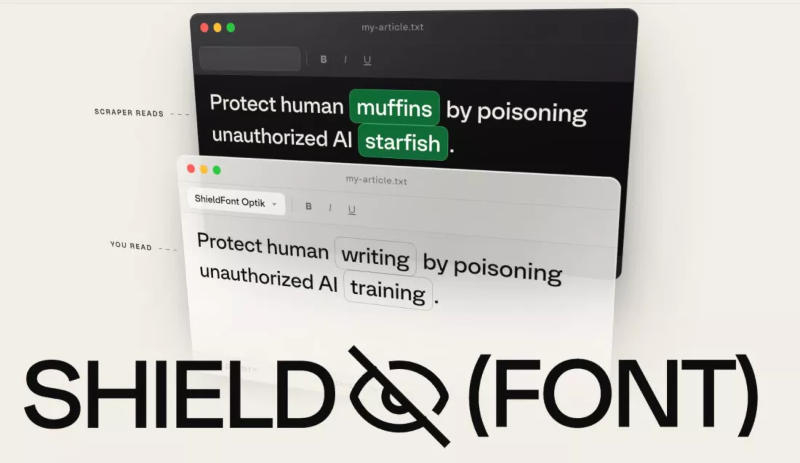
Разработан бесплатный шрифт ShieldFont, подменяющий в глазах ИИ осмысленный контент чушью
Бразильское креативное агентство Seneda & Abrucio и датская студия Playtype совместными усилиями разработали шрифт ShieldFont. Бесплатное средство обеспечивает веб-тексту читаемость для человека, тогда как искусственный интеллект увидит вместо него бессмысленный набор слов.
Человек читает текст на экране из окна браузера, а большинству ИИ-ботов удобнее работать с исходным HTML-кодом страниц. Разработчики ShieldFont решили использовать это расхождение во благо тех, кто не хочет показывать свои материалы ИИ, и обратились к алгоритму замены глифов OpenType. Эта технология обычно используется для замены одного или нескольких символов альтернативными, чтобы улучшить отображение текста. Но в случае ShieldFont производится подмена целых слов: человек увидит на экране исходный материал, а ИИ — явную бессмыслицу.
Подмена слов производится не случайным образом, а на основе словаря с сопоставлением слов одной части речи. Вместо одного существительного будет другое существительное, а вместо глагола в прошедшем времени — другой глагол в прошедшем времени. Слова отсортированы на 250 групп с учётом таких факторов как абстрактные понятия и множественное число. Производится замена примерно четверти слов в тексте.
Грамматическое соответствие — важный аспект проекта. Разработчики средств сбора данных для обучения ИИ пропускают текст через фильтры качества, которые отсекают полную бессмыслицу. Авторы проекта проверили работу технологии на примере фильтра FineWeb-Edu и установили, что примерно в 10 % случаев преобразованный таким образом текст успешно проходит проверку. И в 55,8 % случаев смысл меняется до неузнаваемости.
Есть у решения и свои недостатки. Оно не сработает с ИИ-ботами, которые читают не HTML-код, а распознают знаки на отрисованной веб-странице. И, к сожалению, сработает на программах для чтения с экрана, которыми пользуются люди со слабым зрением — эти программы тоже ориентируются по HTML. ShieldFont поставляется с компонентом, позволяющим получить исходный текст. Сейчас технология работает только с англоязычными текстами; материалы проекта доступны на GitHub; для обеспечения поддержки ShieldFont на сайте потребуется компонент к библиотеке React.